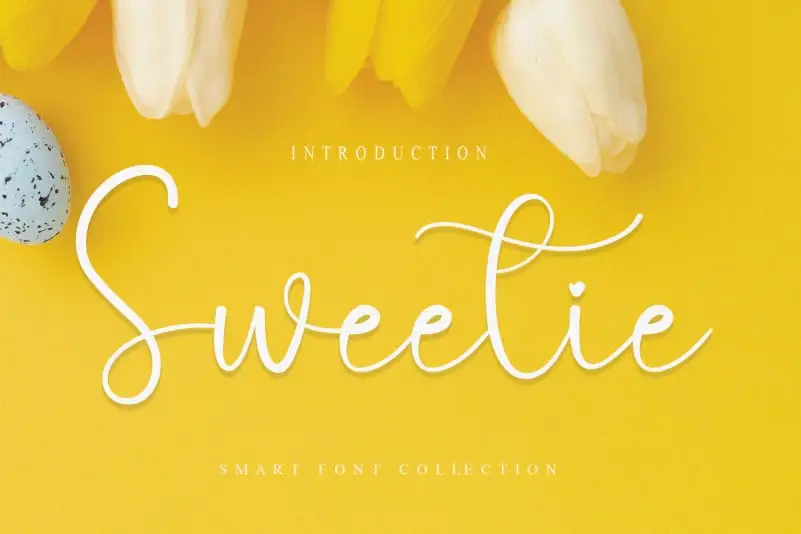
Sweetie Calligraphy Font – Download Grátis
Sinta-se à vontade para explorar a Sweetie Calligraphy Font com uma experiência que vai surpreender seus olhos e impressões digitais. Inspirada em cópias manuscritas autênticas, esta fonte elegante é um verdadeiro alívio para o olho do designer. Seja você criativo ou mais tradicional, a Sweetie Calligraphy é perfeita para personalizar qualquer projeto de design gráfico. Com uma aparência retrô e delicada, essa fonte vem com várias opções de estilo e tamanho que permitem um controle refinado sobre o design final do seu documento. Estamos ansiosos para ver como você vai usá-la em sua próxima obra de arte digital! Sua escolha pode transformar a aparência de qualquer texto ou logomarca, tornando-as uma peça chave no conjunto da sua identidade visual. Sweetie Calligraphy é perfeita para quem busca um estilo elegante e reconfortante na sua composição, seja você criando cartazes, desenhando elementos de marca ou redigindo anúncios. Sua design cuidadoso foi pensado para dar vida a qualquer projeto, oferecendo um toque delicado que complementa e ilumina seu trabalho.